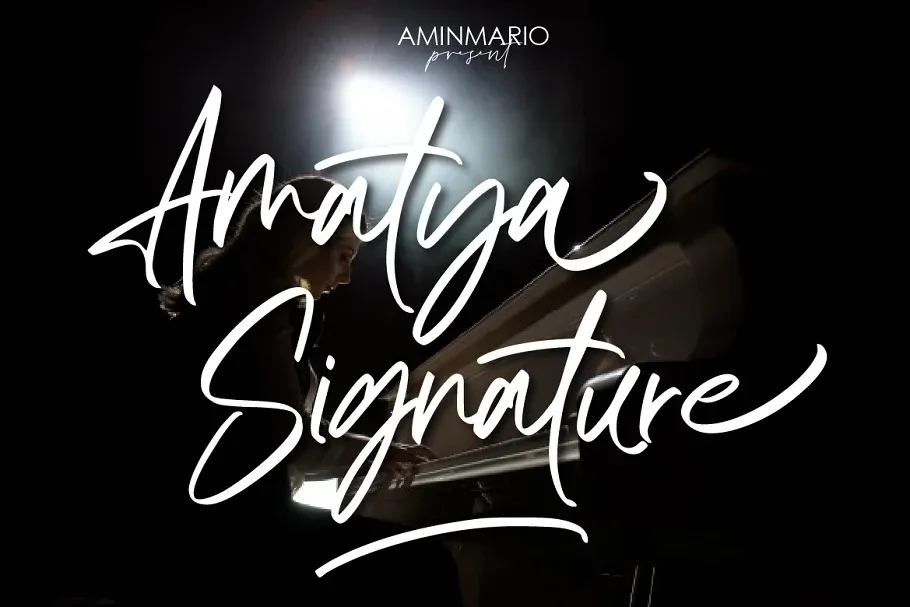
Amatya Signature Font
A Amatya Signature Font é uma escolha perfeita para quem busca um touch delicado e encantador no design. Desenvolvida pelo designer aminmario, essa fonte script tem um toque feminino que enriquece qualquer projeto. Seus traços suaves e expressivos permitem criar mensagens carinhosas e sensuais sem comprometer a legibilidade. O melhor? Ela vem integrada com as funcionalidades OpenType, o que significa que ela se move e viverá como se você estivesse escrevendo por conta própria. Uma vez instalada em seu sistema de design, é uma fonte para quem quer um toque adicional de feminilidade e encanto em seus trabalhos. Perfecta para aqueles momentos especiais ou quando simplesmente deseja deixar uma impressão única. Experimente a Amatya Signature Font e veja como ela pode trazer vida à sua marca, seja ela editorial, gráfica ou digital.